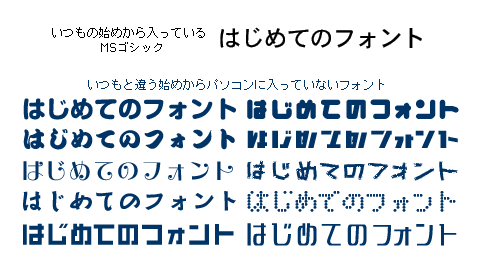
[フォントって何?]
フォントって何なのかわからない人はぜひ読みましょう。 |
「フォント」という言葉を始めて耳にする人、もしくは聞いたことあるけどよくわからない、そんな人も多いかもしれない。なにしろ、フォントという言葉が浸透してまだ数年だからだ。知らなくても当然。
「フォント」は「FONT」という英語のカタカナ表記だ。だから、わかりにくい。もっとやさしく日本語に訳せば「文字」とか「活字」ということだ。つまり今読んでるパソコンなどの文字のこと。
別に、知らなくても問題なくパソコンは使える、でも知っておくともっと「かっこよく」パソコンが使えたり、もっと「かっこいい」企画書が作れたりする。だからぜひ、知っておくべきなのだ。例えば、車だって詳しく知らなくても運転できるけど、多少知っておくと役に立ったり、もてたりするでしょ。
じゃあ、具体的にどんなかっこいい事ができるの?問題はそこ。簡単に言えば、文字を目立たせたり、格好良くできたり、かわいくできたりします。電車の中の広告や雑誌やCDなどで、かっこいい文字を見たことがありませんか?アレもフォントのおかげの可能性大!プロのデザイナーはガンガン「フォント」を使いこなす天才なのです。
| 本当にそんなに簡単に、かっこよくできるのかと思う人もいるかもしれない。大丈夫、簡単です。フォントはフォントの種類を変えるだけなので、どんなパソコンの操作よりもシンプル&簡単なのです。ただし、フォントにはたくさんの種類があります。そこが曲者。なにしろ世界中には1万種以上、日本語でも1000種類以上もあるからです。 |